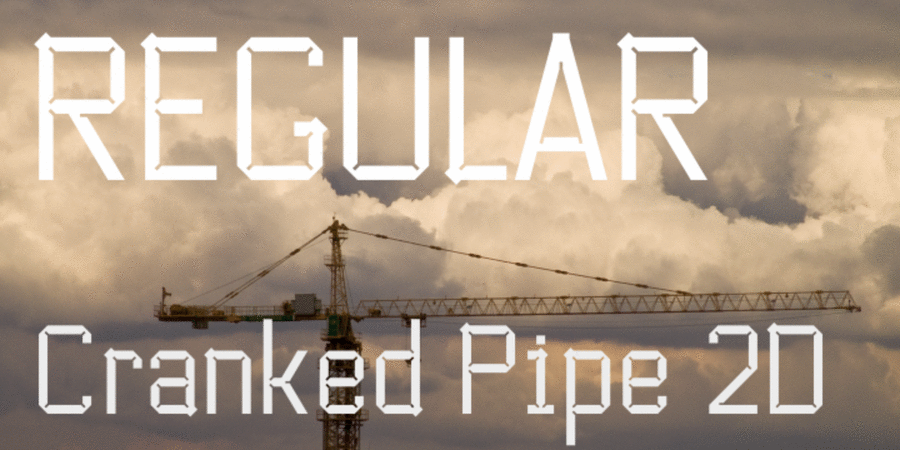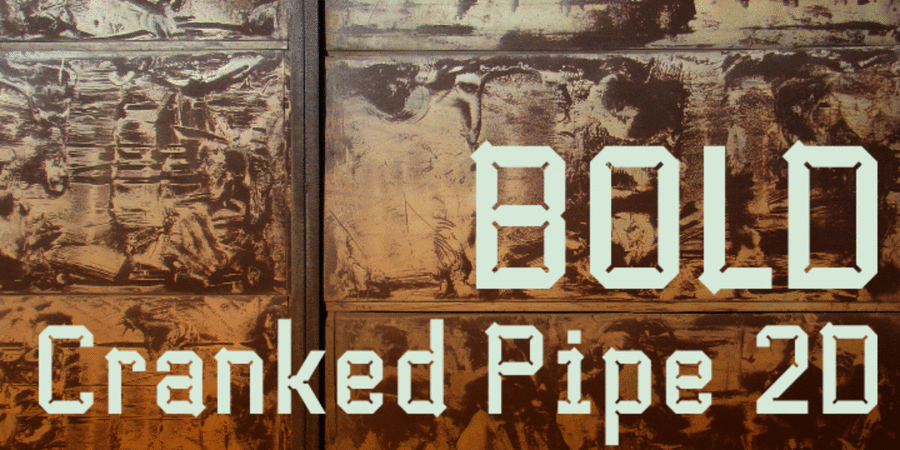
Шрифт Cranked Pipe має індустріальні мотиви та простий модульний геометричний рисунок. Він призначений для роботи у великих розмірах, наприклад, в міській суперграфіці. Cranked Pipe містить символи багатьох мов на усі випадки життя, багато лігатур, альтернативи, розчерки й інші опентайп-фічи. Шрифт розробив Лук'ян Турецький у 2011 році.
Асоціації з сімейством шрифтів Cranked Pipe 2DОсобистість і характер гарнітури:
ламаний, характерний, незграбний, яскравий, ігровий, твердий, статичний, залізний, сталевий, рівний, стійкий, економний, щільний, прямокутний, індустріальний, техногенний, урбаністичний, грубий, побутовий, міський, чіткий, різкий, логічний, штучний, машинний, інженерний, креслярський, архітектурний, оригінальний, шорсткий, гострий, електронний, матричний, рубаний, експериментальний, важкий, суворий, портовий, небезпечний, серйозний, переконливий, надійний, мужній, впевнений, сильний, кондовий, брутальний, військовий, армійський, солдатський, робочий, мотивуючий, жорсткий, зухвалий, екстремальний, хуліганський, радикальний, запальний
гра, верстат, інструмент, конструктор, креслення, інженер, техніка, промисловість, урбаністика, Місто, прилад, фантастика, наука, гаджет, девайс, айтішник, айті, IT, технології, космос, архітектура, дизайн, робот, електроніка, авто, боєприпас, пожежний, оборона, МНС, нафта, кран, шутер, охорона, захист, цегла, вантажівка, війна, армія, зброя, машинобудування, шахта, завод, металургія, будівництво, будматеріали, тара, склад, порт, ящик, патрони, електростанція, енергетика, ремонт, депо, шахтар, шолом, уніформа, вагон, танк, страйкбол, блокбастер, бойовик, екшен, тренажери, автоматика, сталевар, мотор, двигун, залізниця, робочий, реп, концерт, комп'ютерна гра Гарнітура має ознаки стилів: